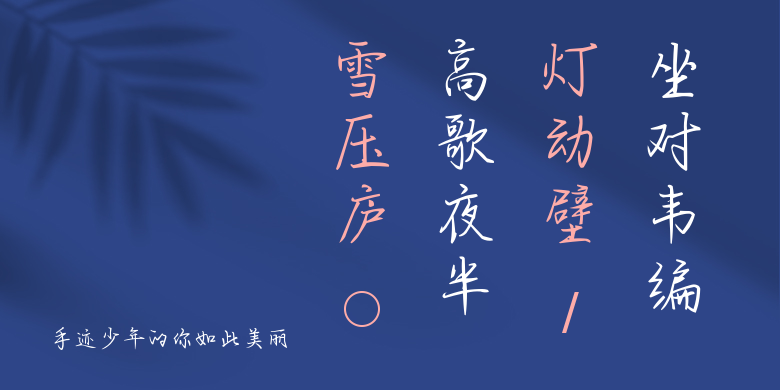
手迹少年的你如此美丽
手迹少年的你如此美丽,这款字体结构工整、笔画清晰,兼顾美观与易读性,适用于标题、正文、海报、包装、LOGO 等多种场景。字形优雅稳定,风格百搭耐看,适配日常排版与创意设计,让文字呈现更舒适、更具质感。手迹少年的你如此美丽一笔一画,皆是细节,以均衡的比例、流畅的线条打造舒适视觉体验,字形端正大气,风格简约现代。无论是商业设计、品牌宣传还是日常排版,都能轻松驾驭,让文字更有格调与力量。手迹少年的你如此美丽字体下载。